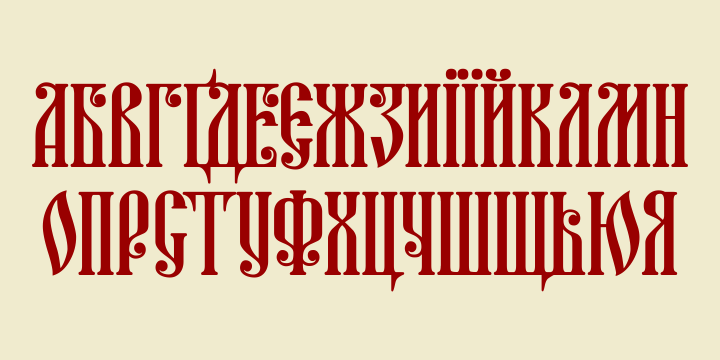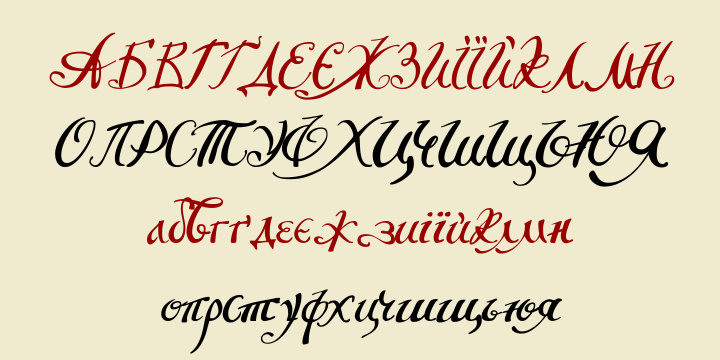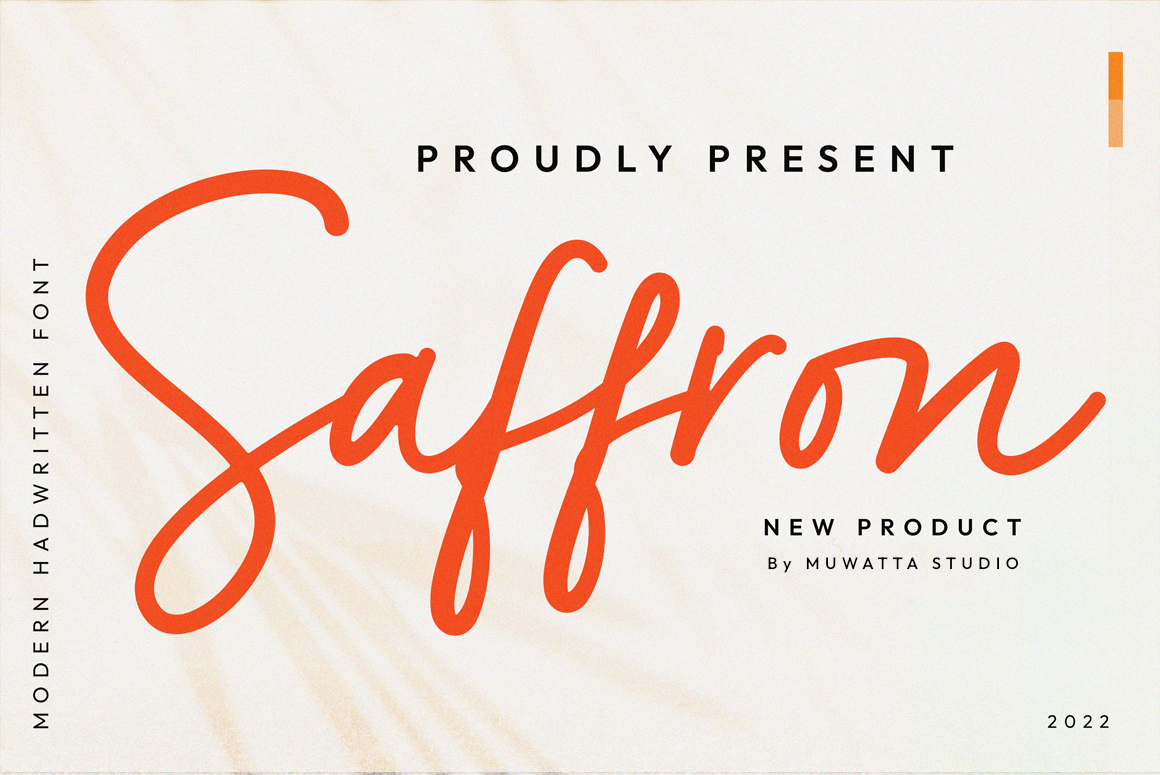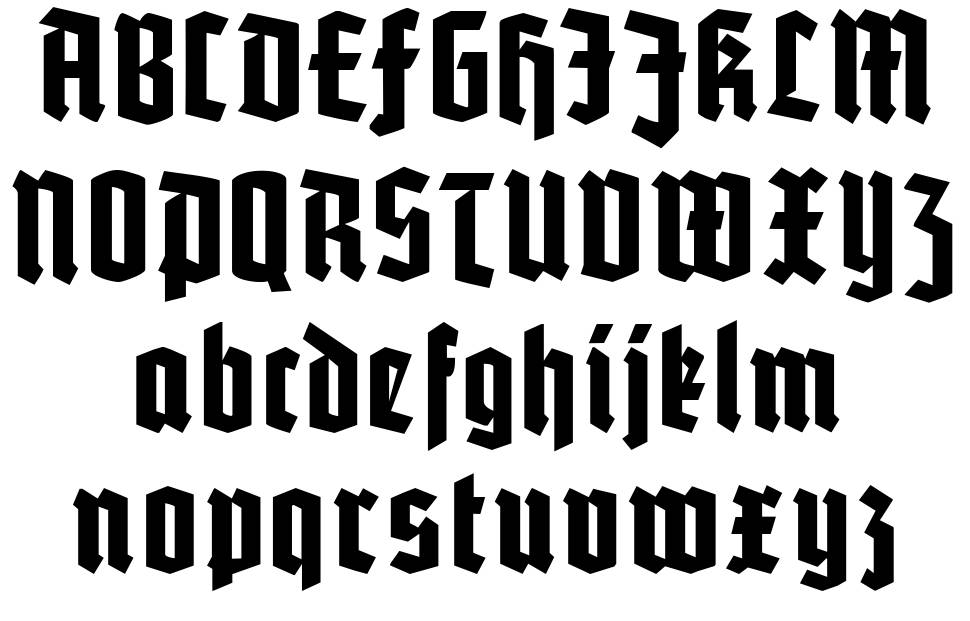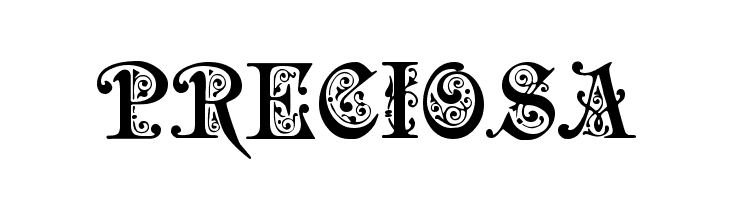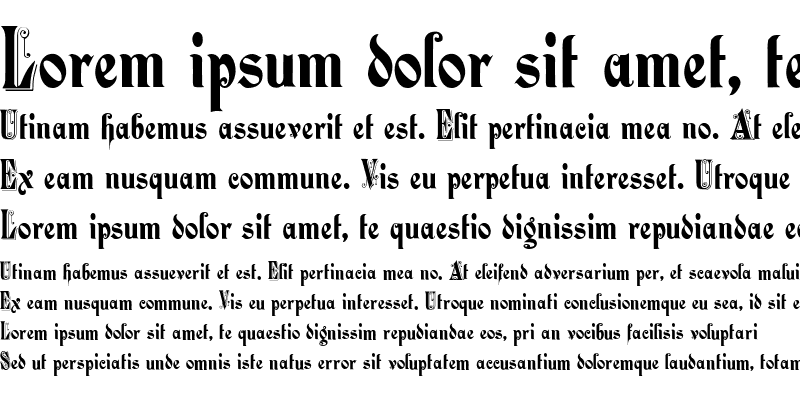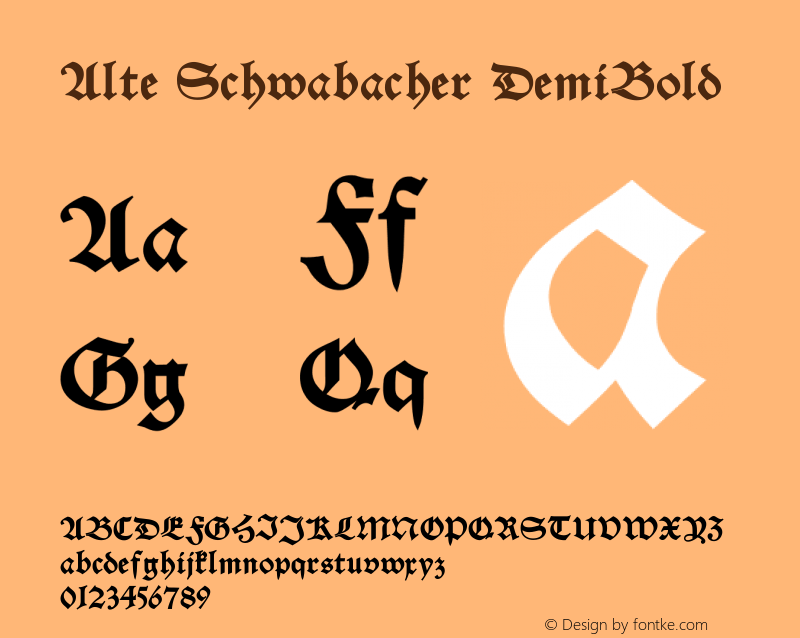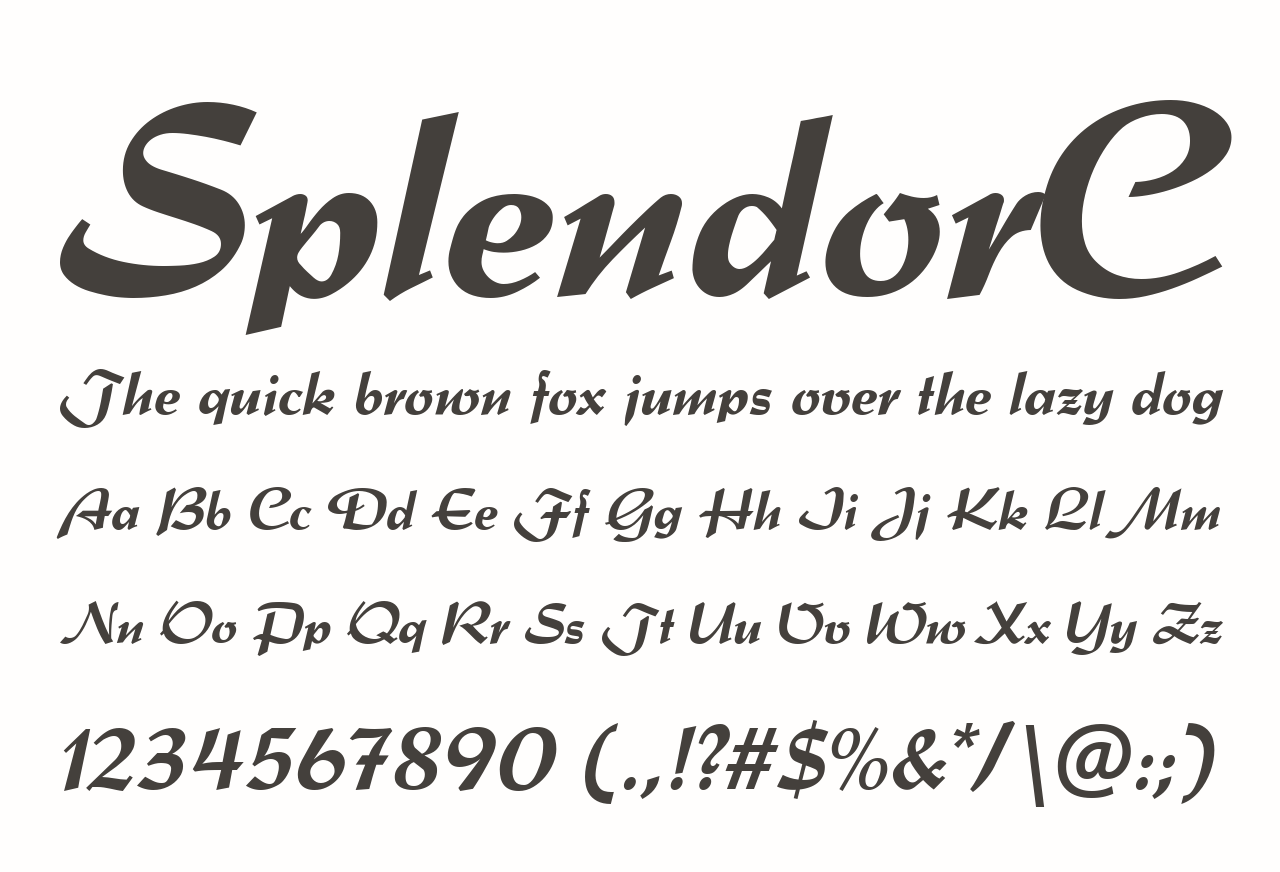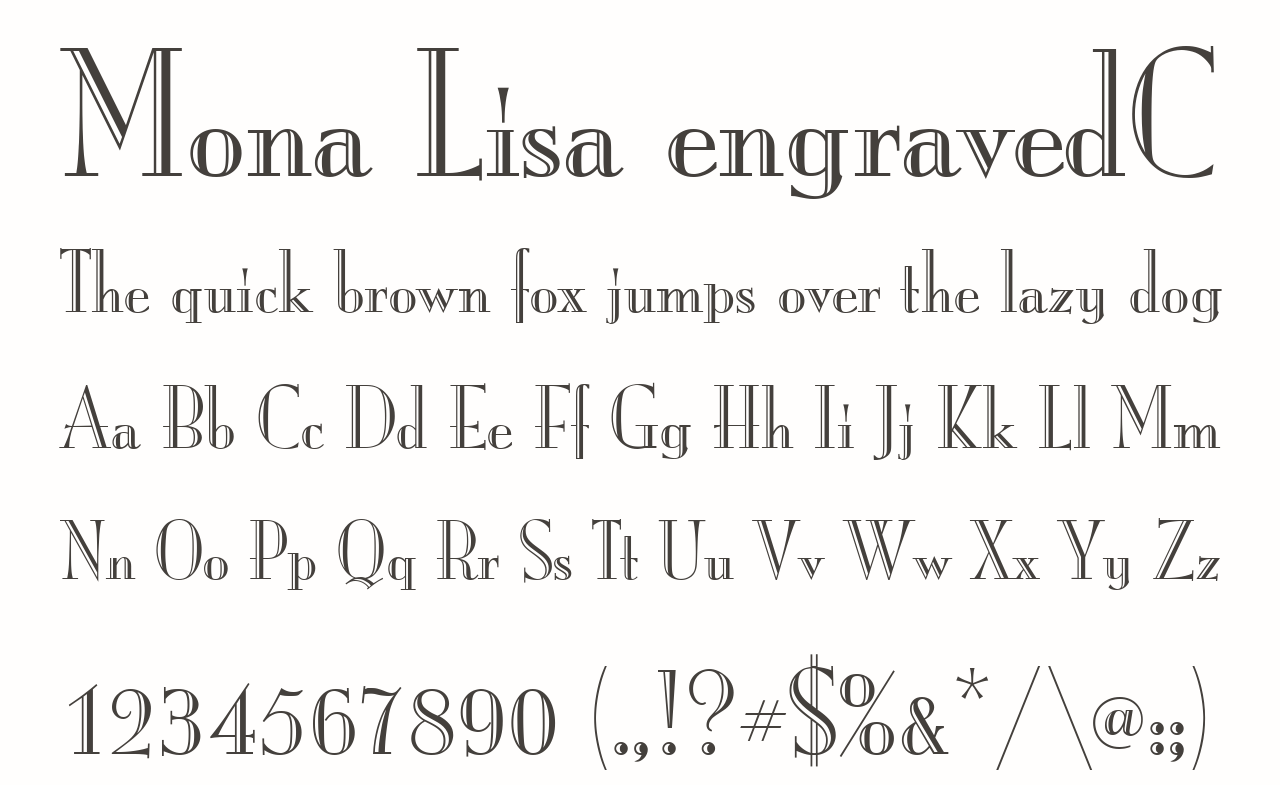
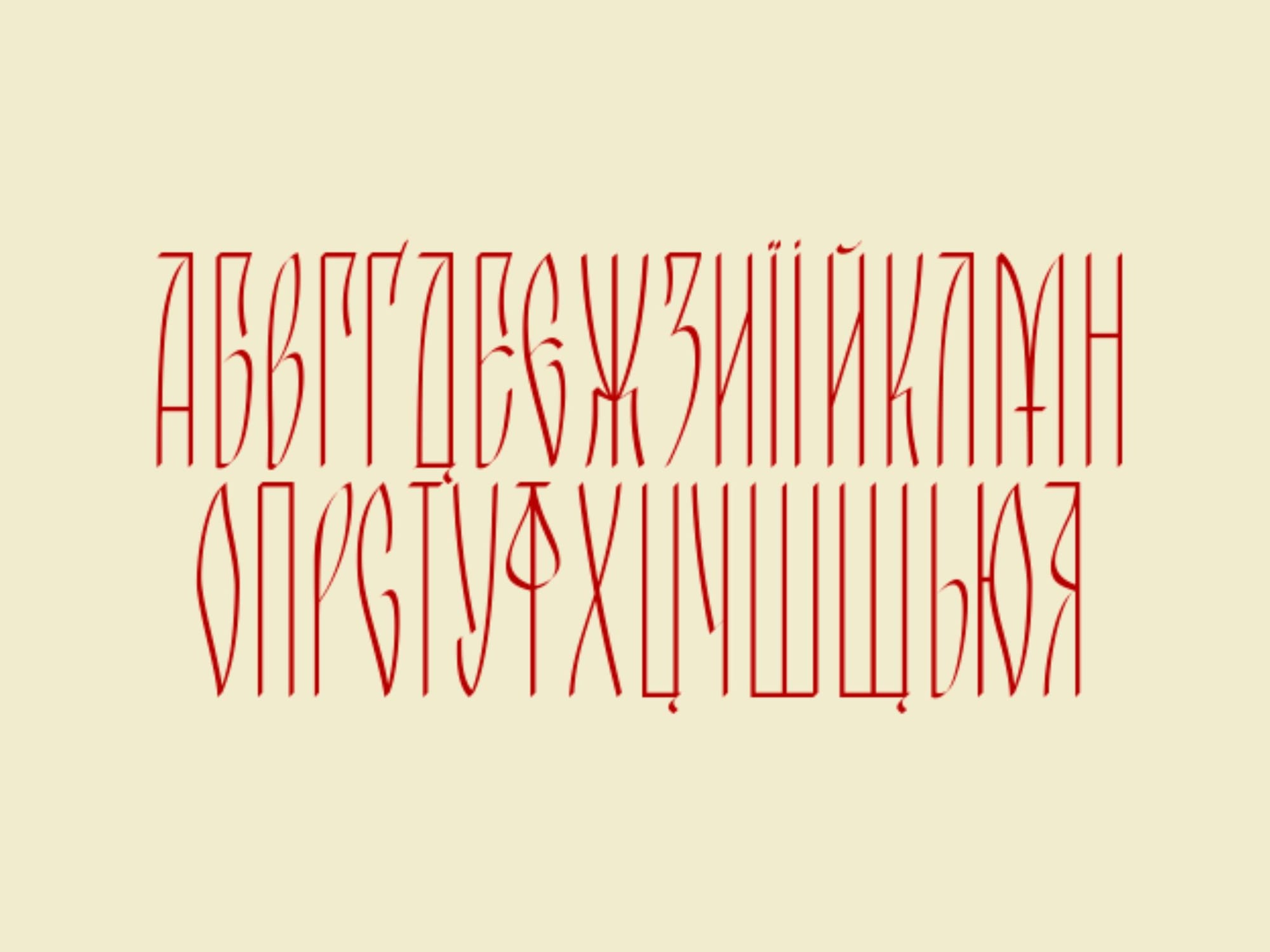
Konstancia
Шрифт Konstancia має класичний та елегантний вигляд. Його використовують для створення вишуканих заголовків та текстів у журналах, книгах або рекламних матеріалах. Шрифт характеризується чіткими, але витонченими лініями, що робить його універсальним для дизайну, який поєднує класичний стиль з сучасними тенденціями.
Schwabacher
Schwabacher – це шрифт із готичними коренями, який розвивався в Німеччині в епоху Ренесансу. Він має чудову виразність, що поєднує елементи стародавнього письма і більш сучасних форм. Schwabacher відомий своєю інтенсивною, майже ірраціональною декоративністю. Використовується в дизайнерських рішеннях для проєктів, які потребують візуальної насиченості.
BehrensKursivC
Шрифт BehrensKursivC є курсивним варіантом шрифту, що вражає своєю вишуканістю. Його форми і лінії виглядають дуже плавно та елегантно, що додає унікального стилю. Цей шрифт, який підходить для використання в текстах, які потребують стилістичної індивідуальності, зокрема для високої моди або преміум-брендів.
Safron Modern
Safron Modern – це шрифт, який поєднує класичну геометрію з сучасним дизайном. Він відрізняється чіткими лініями та збалансованими пропорціями, що дозволяє йому виглядати витончено, але водночас зберігати простоту. Цей шрифт підходить для дизайну вебсайтів, рекламних банерів і публікацій в стилі мінімалізму.
PotsdamC
PotsdamC – шрифт із сильними, виразними формами, які нагадують стиль ар-деко. Його геометричні лінії та чітко виражена структура дозволяють створювати стильні заголовки та акценти. Цей шрифт часто використовують у комерційному дизайні, рекламі або в оформленні обкладинок альбомів та книг.
Preciosa
Preciosa – це елегантний шрифт, що поєднує класичну типографію з витонченими декоративними елементами. Він ідеально підходить для дизайну весільних запрошень, логотипів або брендів, що хочуть підкреслити свою розкіш та елегантність. Завдяки своїм плавним формам, Preciosa створює атмосферу витонченості та стилю.
Romanesque
Romanesque – шрифт, що натхненний архітектурними формами Романського стилю. Його товсті, рельєфні лінії додають текстам монументальності і сили. Це ідеальний шрифт для проєктів, які вимагають більш серйозного та впевненого вигляду, наприклад, для книг, які відображають історичні або культурні теми.
SplendorC
SplendorC – це декоративний шрифт, який використовує безліч вигнутих ліній і елементів, що додають йому витонченості та благородства. Він підходить для проєктів, які повинні бути яскравими і привабливими, включаючи рекламні кампанії, постери або дизайнерські колекції, де важлива візуальна ефектність.
Mona Lisa EngravedC
Mona Lisa EngravedC – шрифт, що відображає витончену красу мистецтва, з елементами, що нагадують гравюри на камені або металі. Він дуже деталізований і має старовинний стиль, що ідеально підходить для проєктів, пов’язаних із мистецтвом або історією. Цей шрифт створює відчуття ретро та класики, що додає особливого шарму тексту.
Mona LisaC
Mona LisaC – ще один шрифт, натхненний класичними гравюрами, але з більш сучасним і лаконічним виглядом. Його відрізняють витончені лінії та форма, що дозволяють використовувати цей шрифт у багатьох дизайнерських напрямках, від книг до висококласних брендів. Цей шрифт привертає увагу своєю елегантністю і чіткістю.